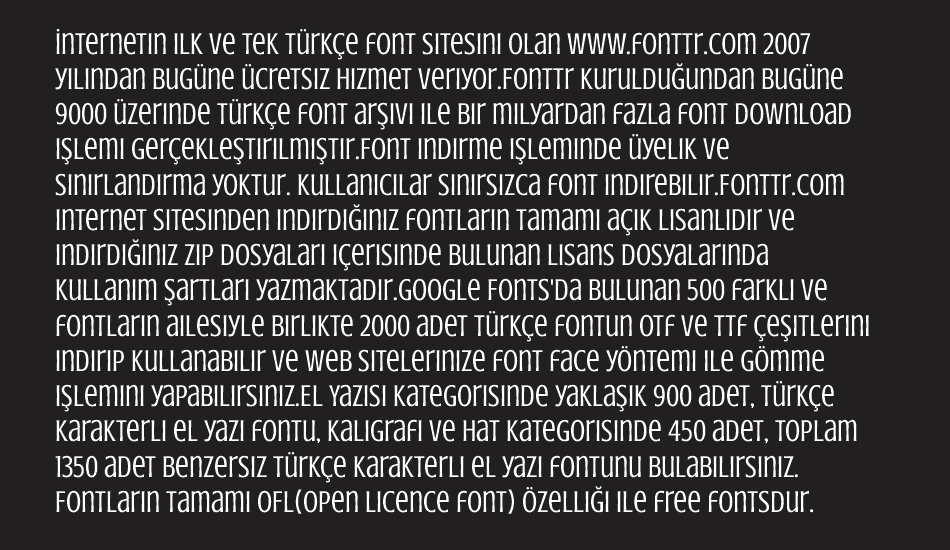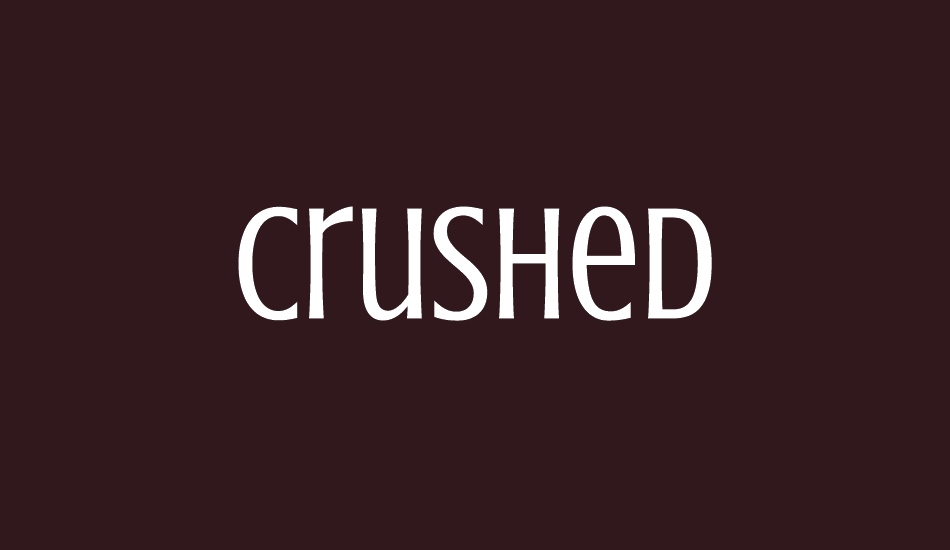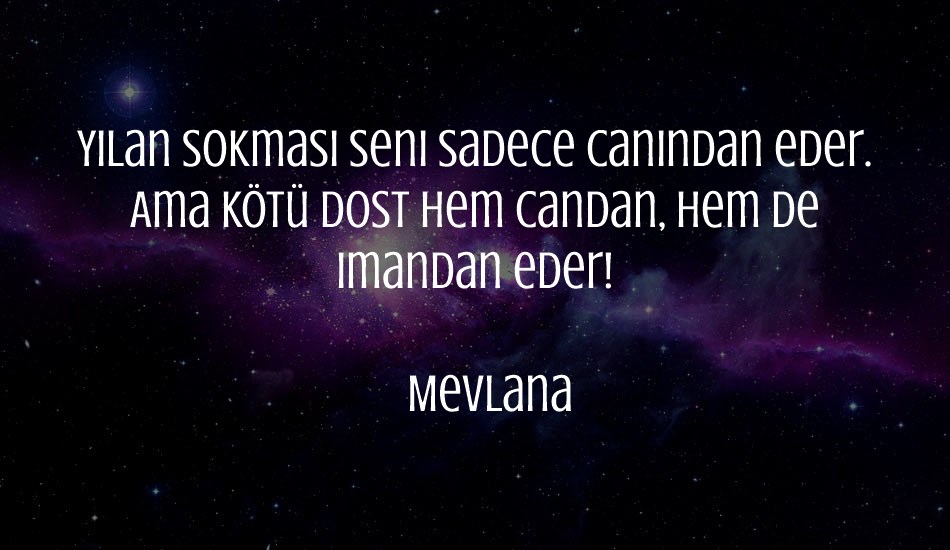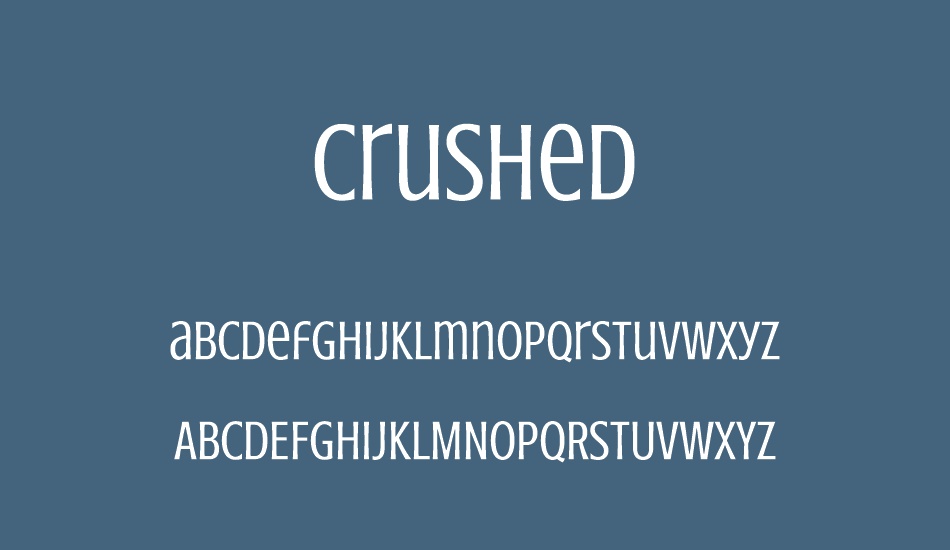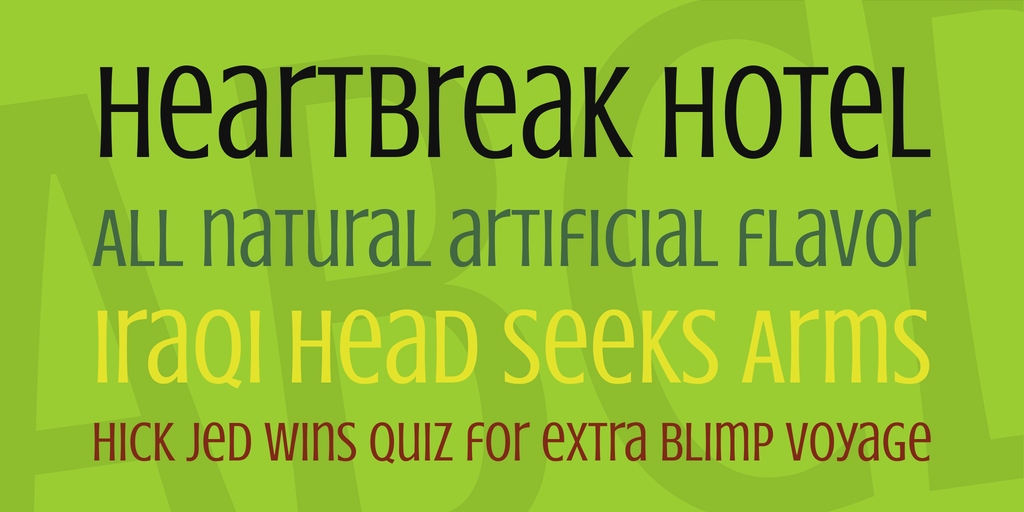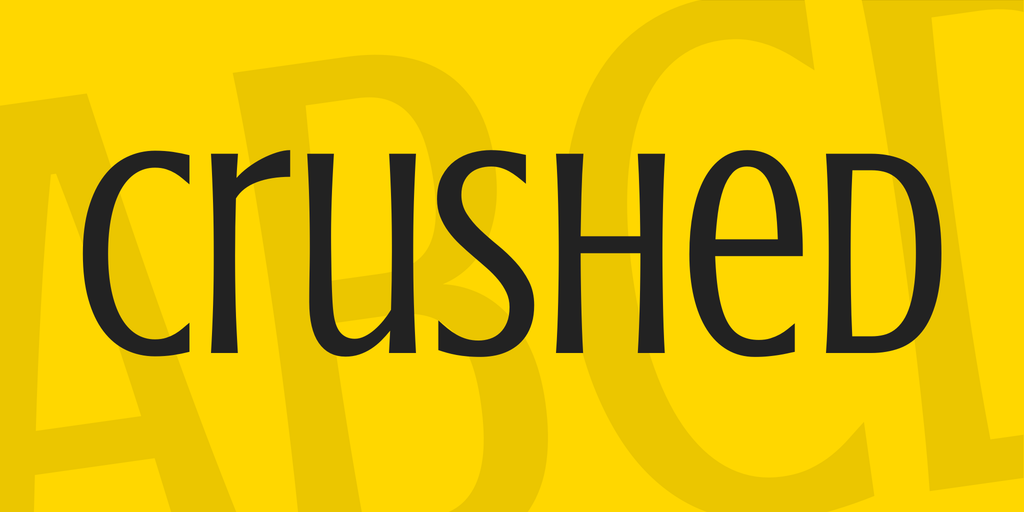
Crushed font
Crushed, 2010 yılında bir başlık ve ekran yazı tipi olarak tasarlandı. Yoğun bir gövde genişliği ve inceltilmiş dikey vuruşlara sahip Crushed, unicase bir tasarım olup, kapak yüksekliğine uyan geleneksel küçük harfi harfine atmaktadır. Gösterime yönelik olsa da, Crushed font aslında harika görünüyor ve metin kullanımında iyi okuyor. Gövdelerin nazik konikliği belirli bir sınıf ekler ve temel harf formları modern ve taze.